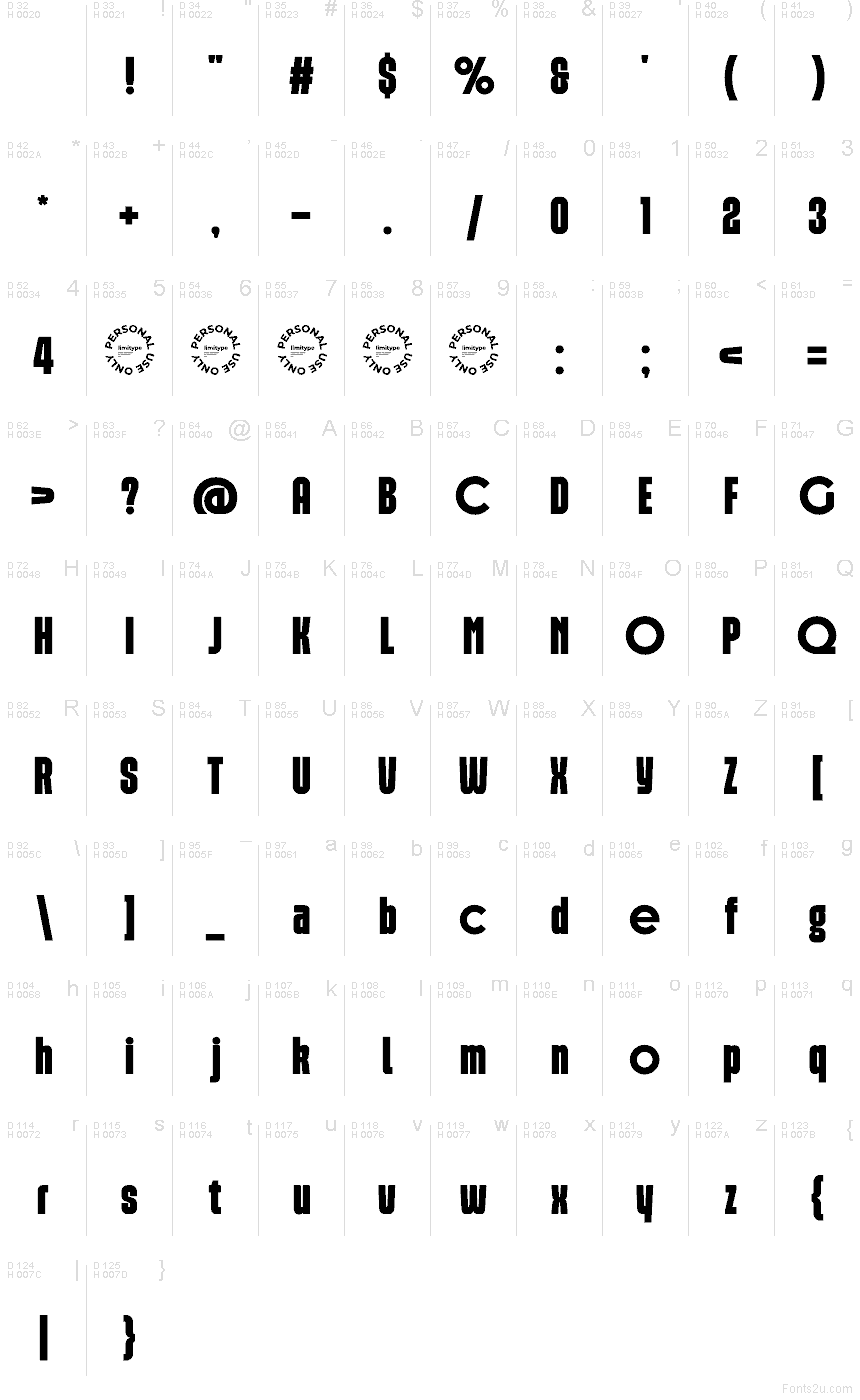
Amover, desenhada por Limitype, é uma fonte sans-serif retro de estilo display gratuita, com formas amplas e arredondadas e uma silhueta densa. Junções apertadas e curvas circulares dão às letras um aspecto compacto.
As letras podem dar às capas de discos um visual de estúdio dos anos 1970, mas a sua geometria limpa também se adapta à identidade visual de marcas de moda contemporâneas. É igualmente adequada para cartazes musicais e gráficos de eventos baseados em tipografia ampliada. No design editorial, pode moldar títulos de capa marcantes para artigos sobre vida noturna, música ou cultura pop.